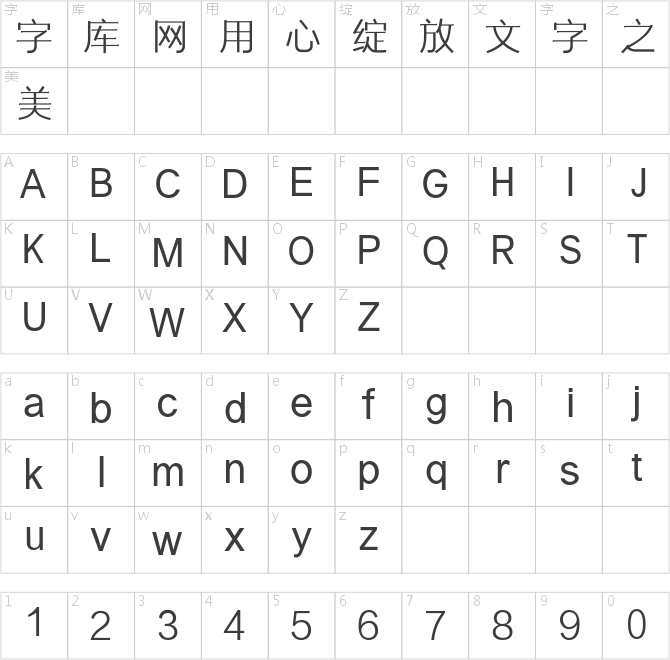
字體名稱: 三極頌黑簡體
三極頌黑簡體
三極頌黑簡體介紹
三極頌黑簡體的頌用了跟宋的同音,此款字的橫豎勾帶有宋體結構,其字形清新,結構嚴謹,布白均勻,結合了宋體飽滿的結構特征,又不失黑體本身的銳利簡潔,精致且富有內涵。
三極頌黑簡體字體SJsonghei字庫是一款讓人賞心悅目、百看不厭的中文字體,適合各類廣告和產品包裝設計應用,字體大小2.27MB,格式為ttf字體,上傳用戶是三極字庫,作者/版權方為三極字庫/夏桑霜